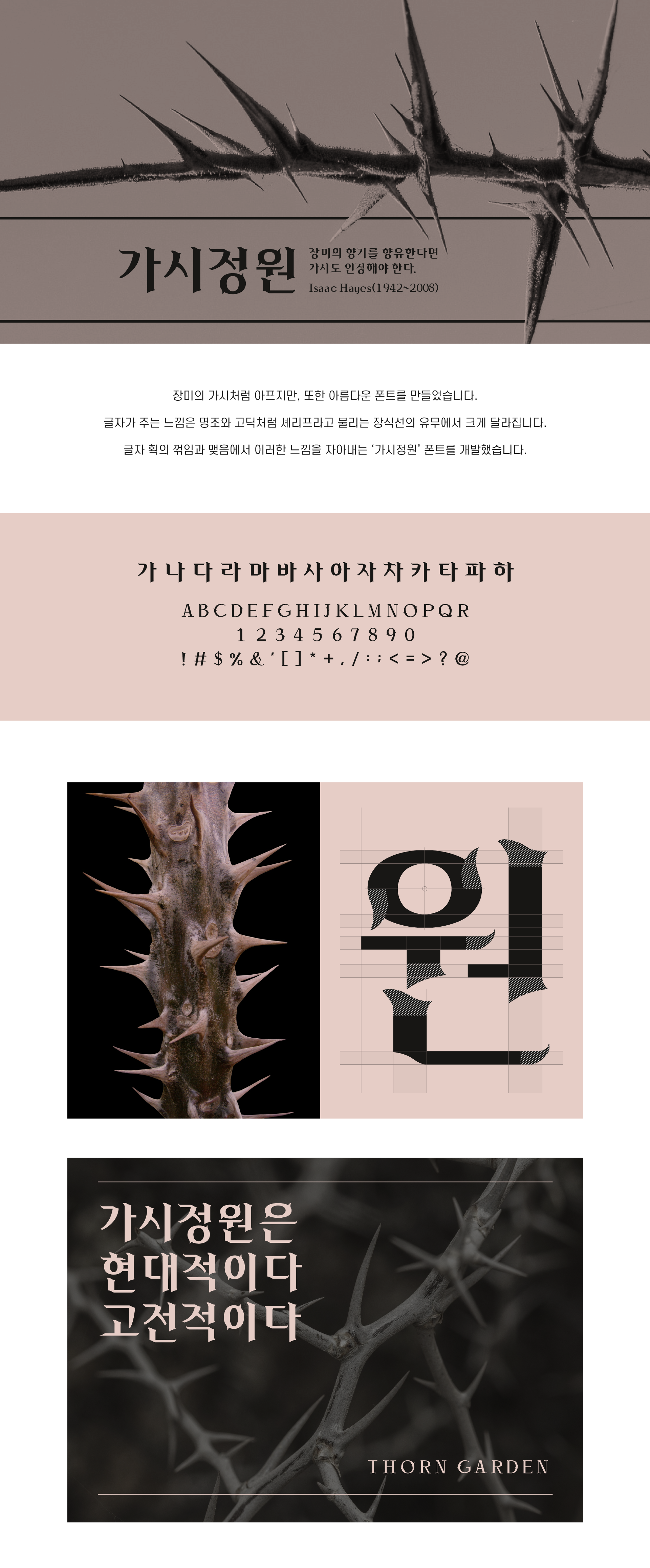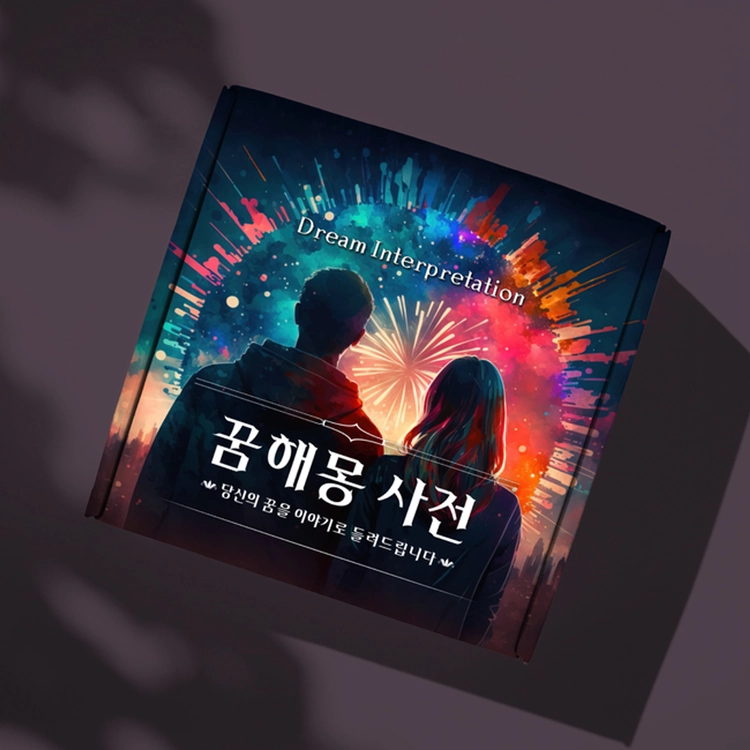
가시정원 2종 세트SALEBEST
장미의 가시처럼 아프지만, 또한 아름다운 폰트를 만들었습니다. 글자가 주는 느낌은 명조와 고딕처럼 셰리프라고 불리는 장식선의 유무에서 크게 달라집니다. 글자 획의 꺾임과 맺음에서 이러한 느낌을 자아내는 '가시정원' 폰트를 개발했습니다.